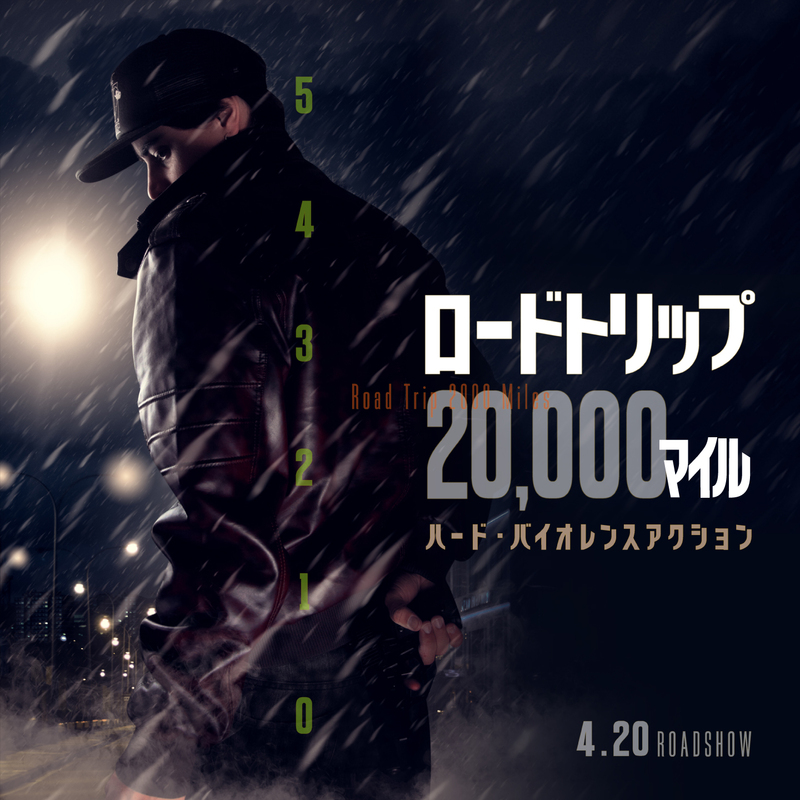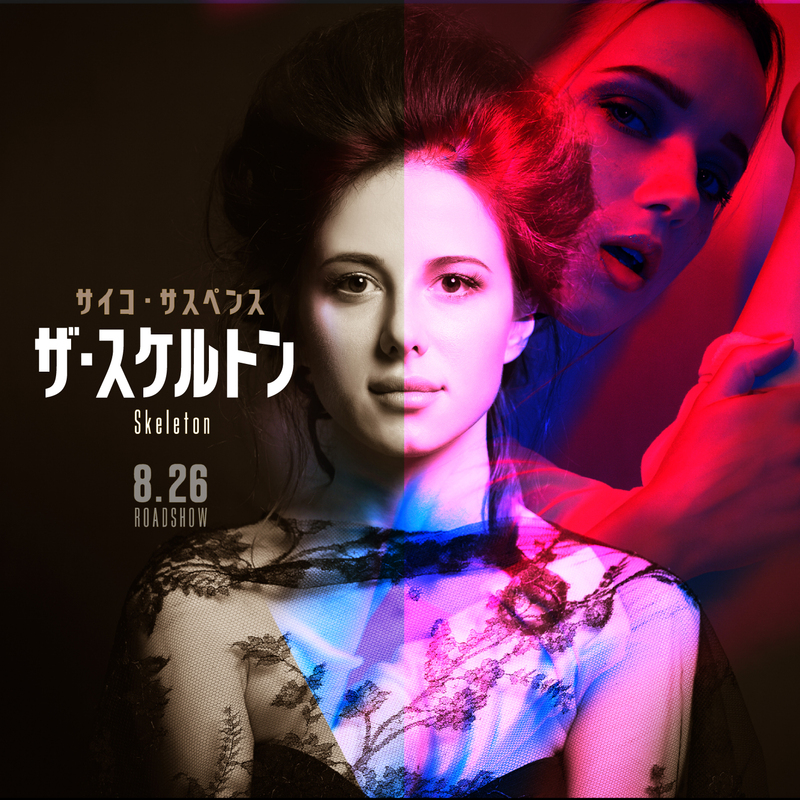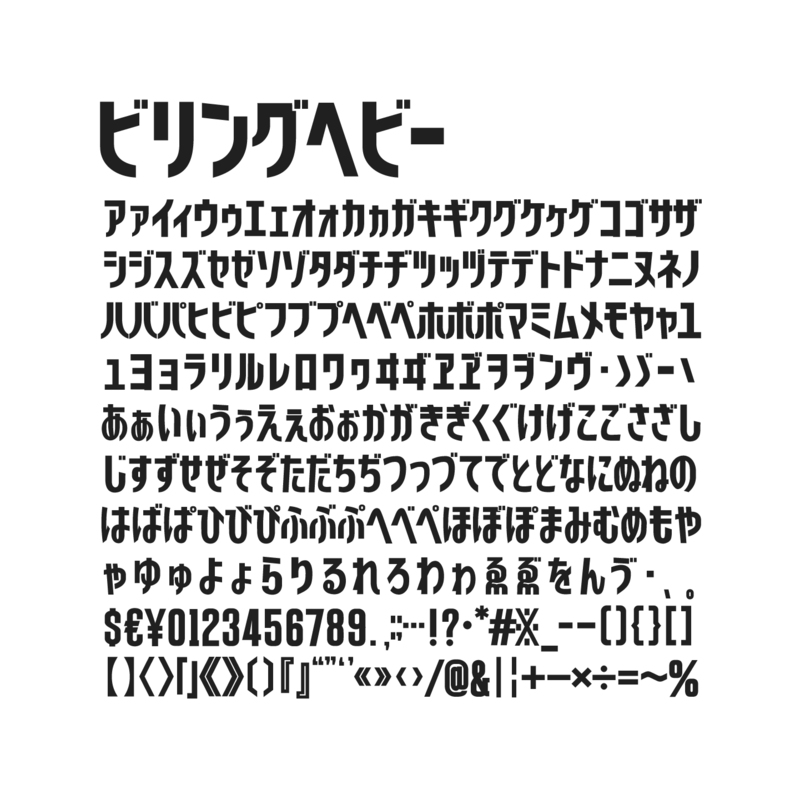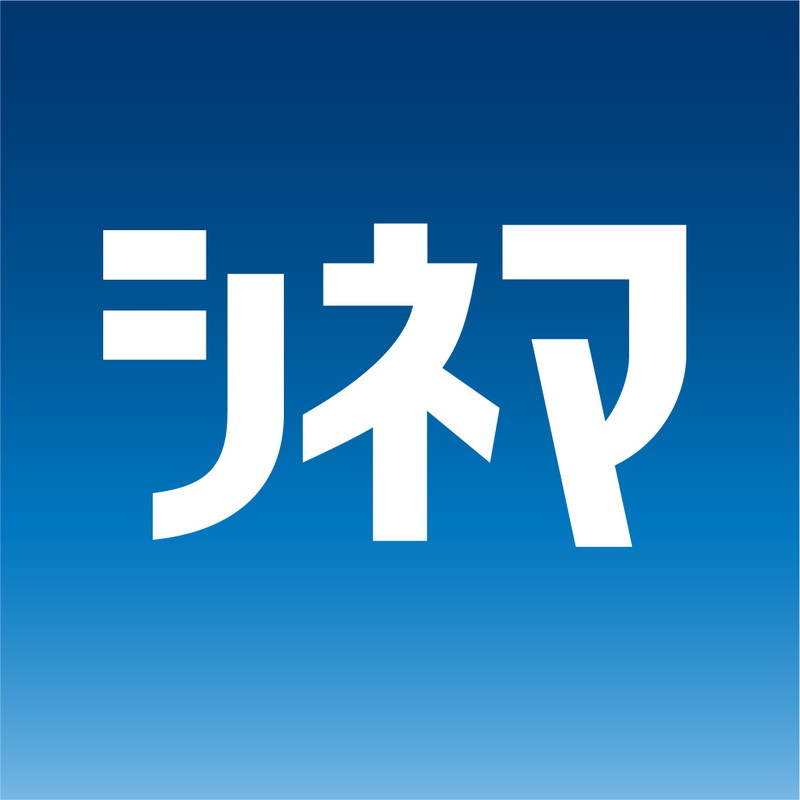
ビリング・ヘビー|Chiba Design|和文・欧文・デザイン書体のダウンロード販売|フォントファクトリー
商用利用可能なオリジナルフォントです。Open Type・ 2バイト・カタカナ&ひらがな、数字、約物。アウトライン化可能。英語のポスタークレジットに使用される長体をアレンジしたフォント。ロゴの作成などに便利です。